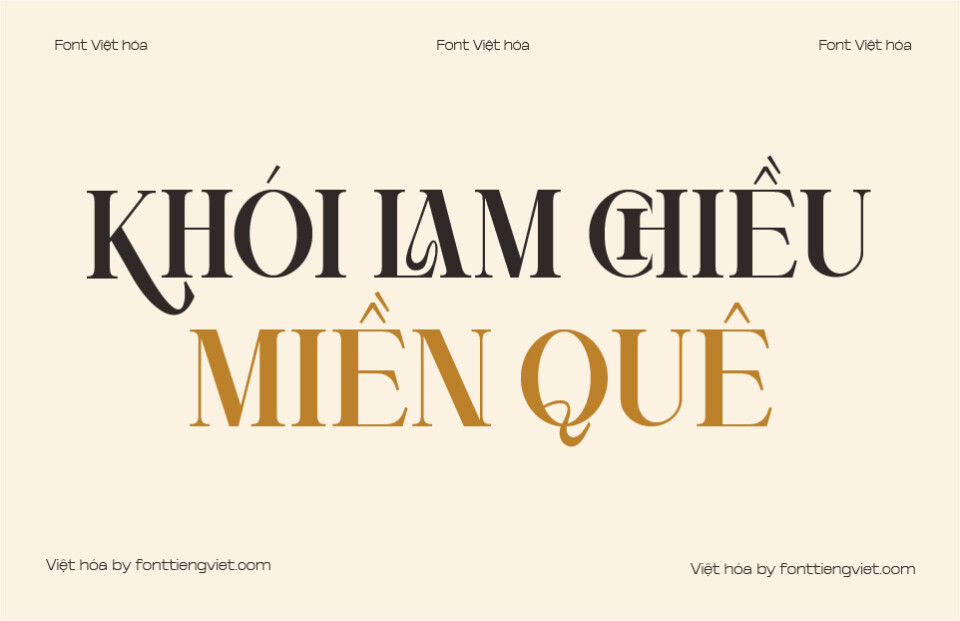
Font Việt hóa 1FTV VIP Lamcho
Trong thế giới thiết kế đồ họa hiện đại, việc lựa chọn một bộ phông chữ phù hợp không chỉ giúp truyền tải thông điệp mà còn khẳng định phong cách cá nhân độc đáo. Font Việt hóa 1FTV VIP Lamcho đang trở thành tâm điểm chú ý của cộng đồng designer nhờ sự kết hợp tinh tế giữa nét chữ cổ điển và tư duy hiện đại. Khi tìm kiếm một Font Miễn Phí để làm mới các ấn phẩm học đường hay dự án cá nhân, bộ font này chắc chắn là ứng cử viên sáng giá nhất. Với khả năng tương thích cao và bảng mã ký tự đầy đủ dấu tiếng Việt, 1FTV VIP Lamcho giúp bạn loại bỏ hoàn toàn nỗi lo lỗi font khi gõ nội dung dài trên các phần mềm thiết kế chuyên dụng như Photoshop hay Illustrator.
Khám phá vẻ đẹp độc bản của Font Việt hóa 1FTV VIP Lamcho
Điều làm nên sức hút của Font Việt hóa 1FTV VIP Lamcho chính là những đường nét thanh mảnh nhưng vô cùng dứt khoát. Bộ chữ được tối ưu hóa để giữ được sự mềm mại cần thiết cho các tiêu đề thơ ca, trong khi vẫn đủ độ dày để tạo điểm nhấn cho các khẩu hiệu tuyên truyền tại trường học. Mỗi chữ cái trong bộ font này đều được chăm chút tỉ mỉ, đảm bảo khoảng cách giữa các ký tự (kerning) luôn đạt độ cân bằng hoàn hảo. Điều này đặc biệt quan trọng đối với các bạn học sinh, sinh viên khi làm slide thuyết trình hoặc thiết kế bìa báo tường, giúp bài làm trở nên chuyên nghiệp và bắt mắt hơn trong mắt thầy cô và bạn bè.
Ưu điểm vượt trội khi sử dụng font chữ trong học tập
Sử dụng Font Việt hóa 1FTV VIP Lamcho mang lại nhiều lợi ích thiết thực cho người dùng cuối. Đầu tiên, đây là một bộ font được tối ưu hóa dung lượng, giúp việc chia sẻ file thiết kế qua email hay các nền tảng mạng xã hội diễn ra nhanh chóng mà không làm nặng máy. Thứ hai, khả năng hiển thị rõ nét trên cả màn hình máy tính và bản in ấn thực tế giúp bạn tự tin xuất bản các tài liệu học tập chất lượng cao. Cuối cùng, tính linh hoạt của font cho phép bạn ứng dụng trong nhiều bối cảnh khác nhau, từ thiết kế thiệp mời, làm video cho đến trang trí các trang blog cá nhân thêm phần sinh động và đầy cảm hứng.